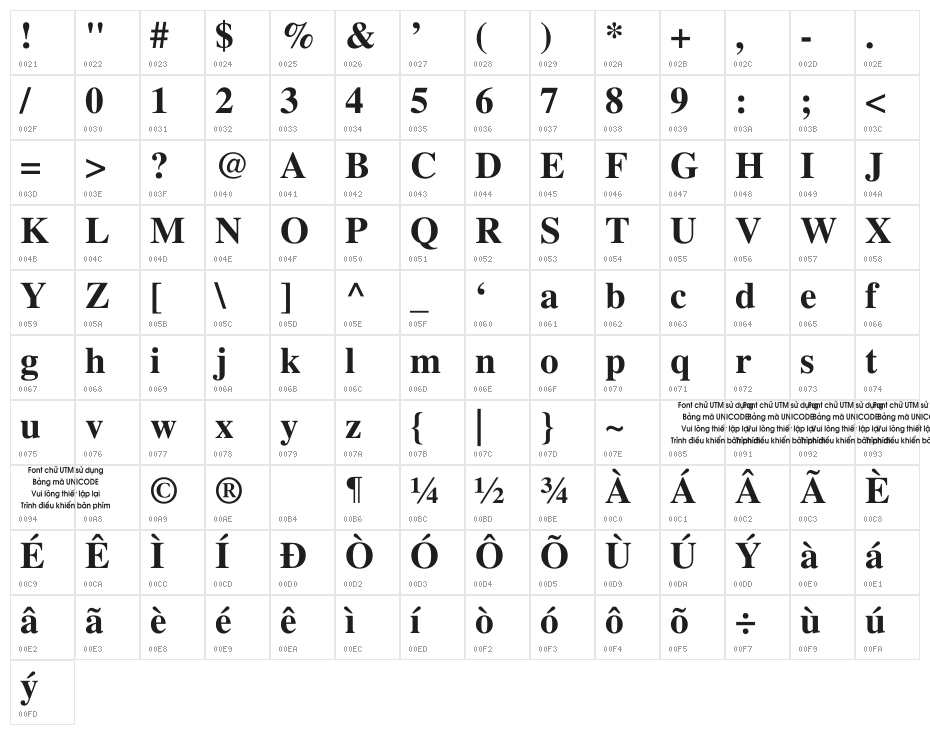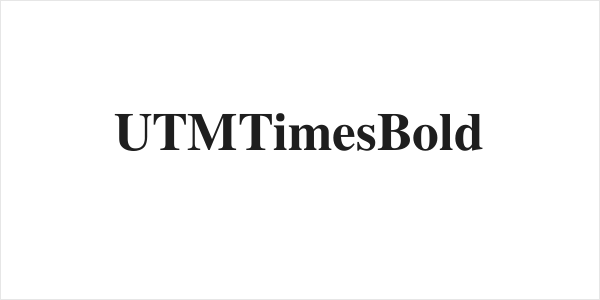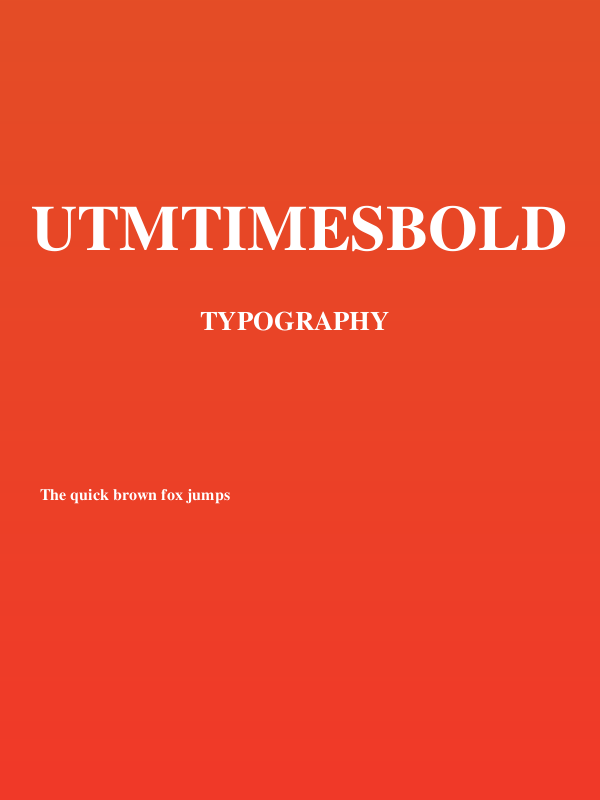
UTMTimesBold Font
✎ Serif
| 整体风格 | Classic |
| 使用场景 | Headlines, Logos, Formal documents |
| 推荐项目 | Ideal for book covers, formal invitations, headlines, and branding materials that require a traditional yet bold appearance. |